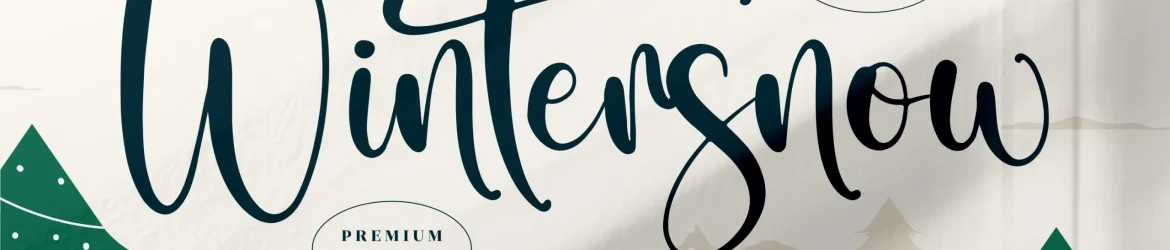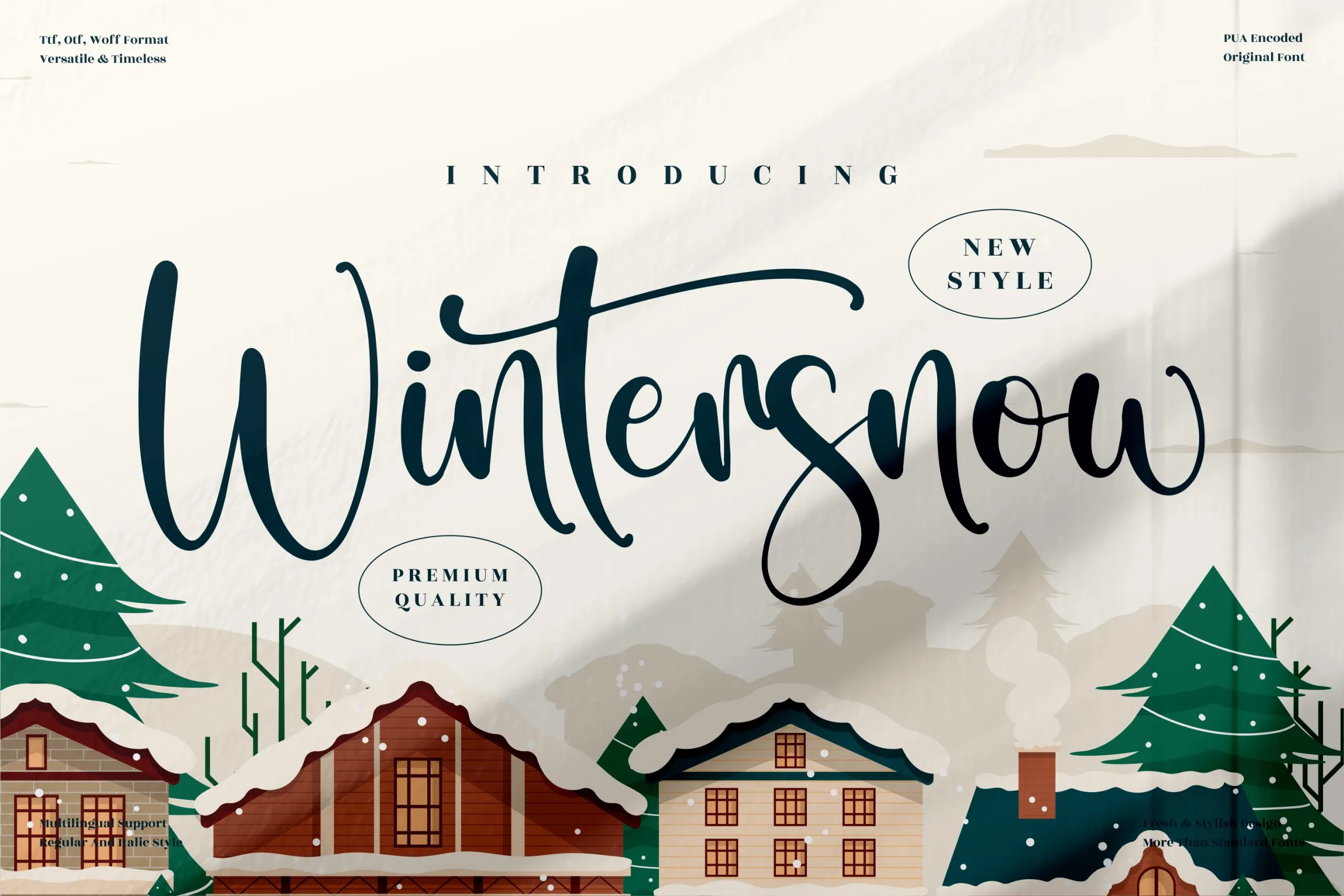
Wintersnow Font – Fonte Grátis
Wintersnow Font
Esta é uma elegante fonte de calligrafia projetada para dar vida a qualquer projeto. Perfeita para trabalhos detalhados como logomarcas, design de marca, objetos de decoração, embalagens de produtos, talheres, cartazes e etiquetas, é perfeita para um leque amplo de ideias criativas que exigem uma escrita elegante. A Wintersnow Font não apenas ilumina seus projetos com seu belo e romântico estilo calligrafia, mas também oferece a você a capacidade de criar experiências únicas e memoráveis para suas campanhas e produtos, sejam eles um tatuagem em uma camiseta ou um cartão de aniversário. Com Wintersnow Font na sua coleção, é como dar vida à arte da palavra, tornando-a parte integrante e vibrante do seu design.